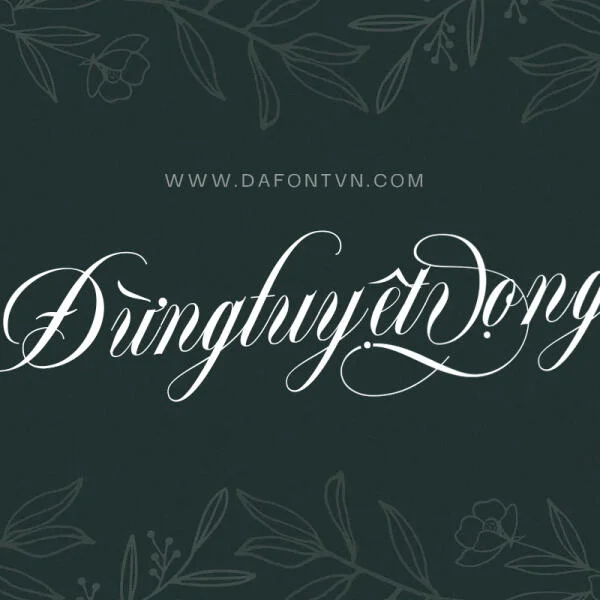
Download Font Blade Rush Việt hóa hiện đại sáng tạo
Tải về font Blade Rush mong phong cách độc lạ và bắt mắt với các chữ cái viết hoa và viết thường đi kèm với các glyph uốn lượn siêu đẹp được thiết kế tỉ mỉ ở cuối bài viết.
Tổng quan về Font Blade Rush
Blade Rush là một phông chữ sans serif với đầy đủ các chữ cái viết hoa và viết thường, các ký hiệu đa ngôn ngữ, số, dấu câu và chữ ghép. Blade Rush Kiểu phông chữ Sans Serif thanh lịch dành cho thiết kế thương hiệu Áp phích, Tạp chí, Làm đẹp với nét vẽ phù hợp với ý tưởng thiết kế thanh lịch đẹp mắt của bạn.
Chi tiết các ký tự font việt hóa Blade Rush